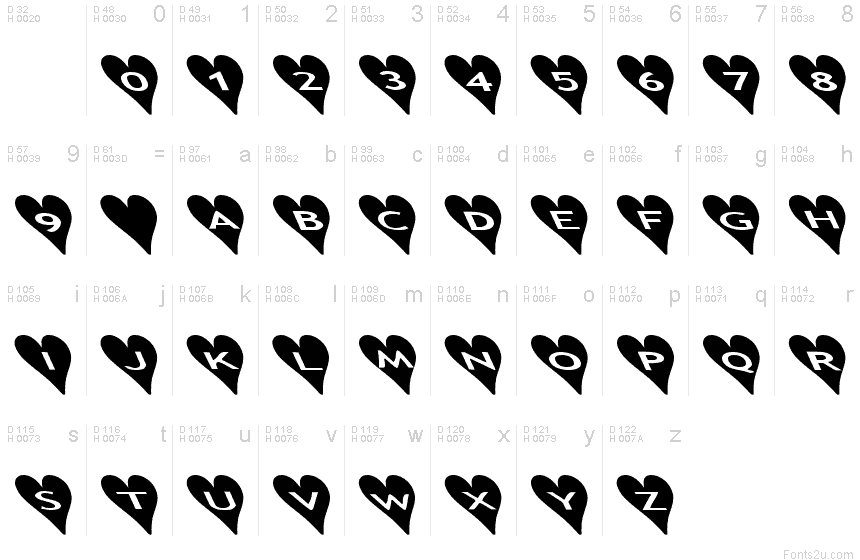
AlphaShapes Hearts 2b od Fonts n Things to darmowy, dekoracyjny krój pisma, w którym litery zamknięto w kształcie serc, nadając im rękodzielniczy, walentynkowy charakter. Znaki są jakby „wycięte” w wyrazistych, pochylonych sercach, dzięki czemu czcionka sprawia wrażenie zestawu graficznych emblematów, a nie zwykłego pisma. Każdy znak opiera się na tej samej miękkiej, masywnej sylwetce.
To naturalny wybór na zaproszenia na przyjęcia, okolicznościowe ulotki, tytuły w albumach, opakowania butikowe czy krótkie wpisy w mediach społecznościowych, gdzie tekst powinien być zwięzły. Jako darmowy font, doskonale sprawdzi się również w monogramach, tytułach na okładkach czy wizytówkach, ponieważ powtarzalny kształt serca nadaje nawet kilku literom wygląd gotowego znaku.